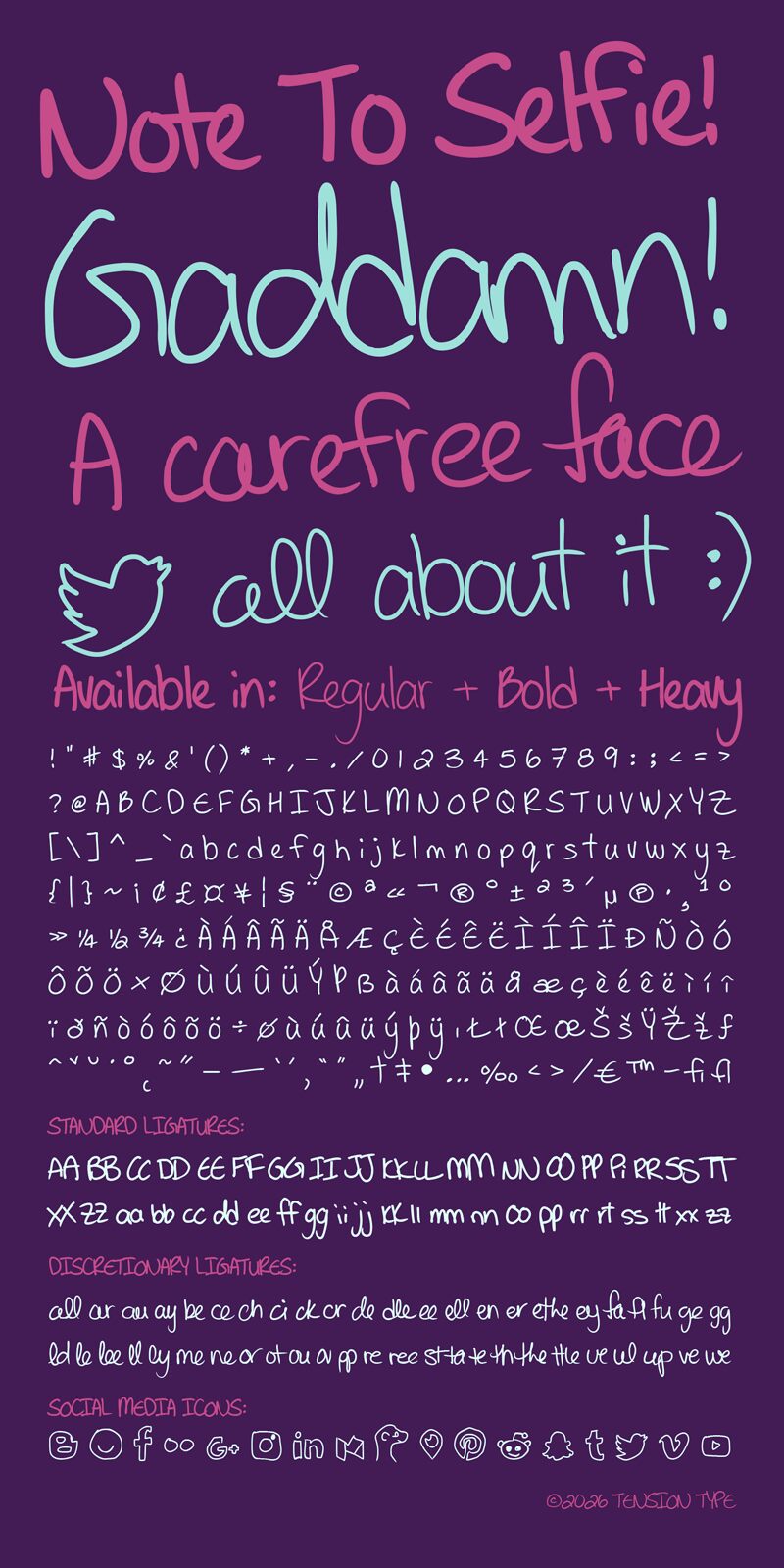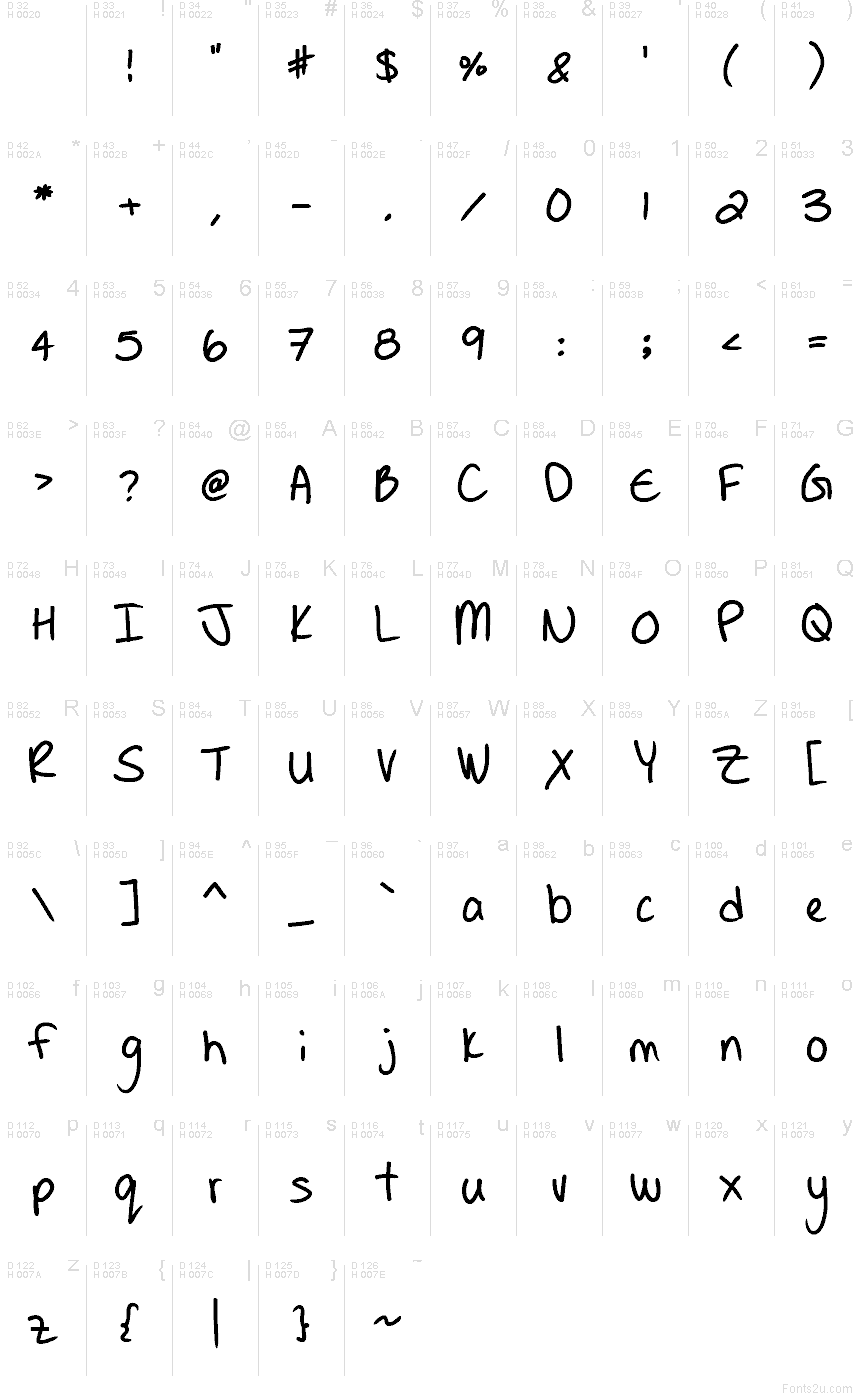
Note to Selfie Heavy di Tension Type è un font scritto a mano gratuito, caratterizzato da tratti ampi simili a quelli di un pennarello e da un movimento sciolto e verticale. Le estremità arrotondate e il tratto leggermente irregolare conferiscono alle lettere l'aspetto di un appunto scritto di fretta, ma lo spessore costante del segno mantiene il tutto coeso ed elegante.
Questo equilibrio lo rende una scelta naturale per copertine di diari, grafiche con citazioni, adesivi, packaging informali e intestazioni per i social media. È perfetto anche per materiali scolastici o progetti di branding amichevoli, dove una texture che richiama la scrittura a mano risulta decisamente più credibile di un font troppo formale.
Un altro font scritto a mano tra cui scegliere. Può sembrare un po' impreciso, ma ha un aspetto autentico. Non è il risultato di un veloce tracciamento automatico; ci ho lavorato a lungo. Spero che sia perfetto per il tuo progetto.